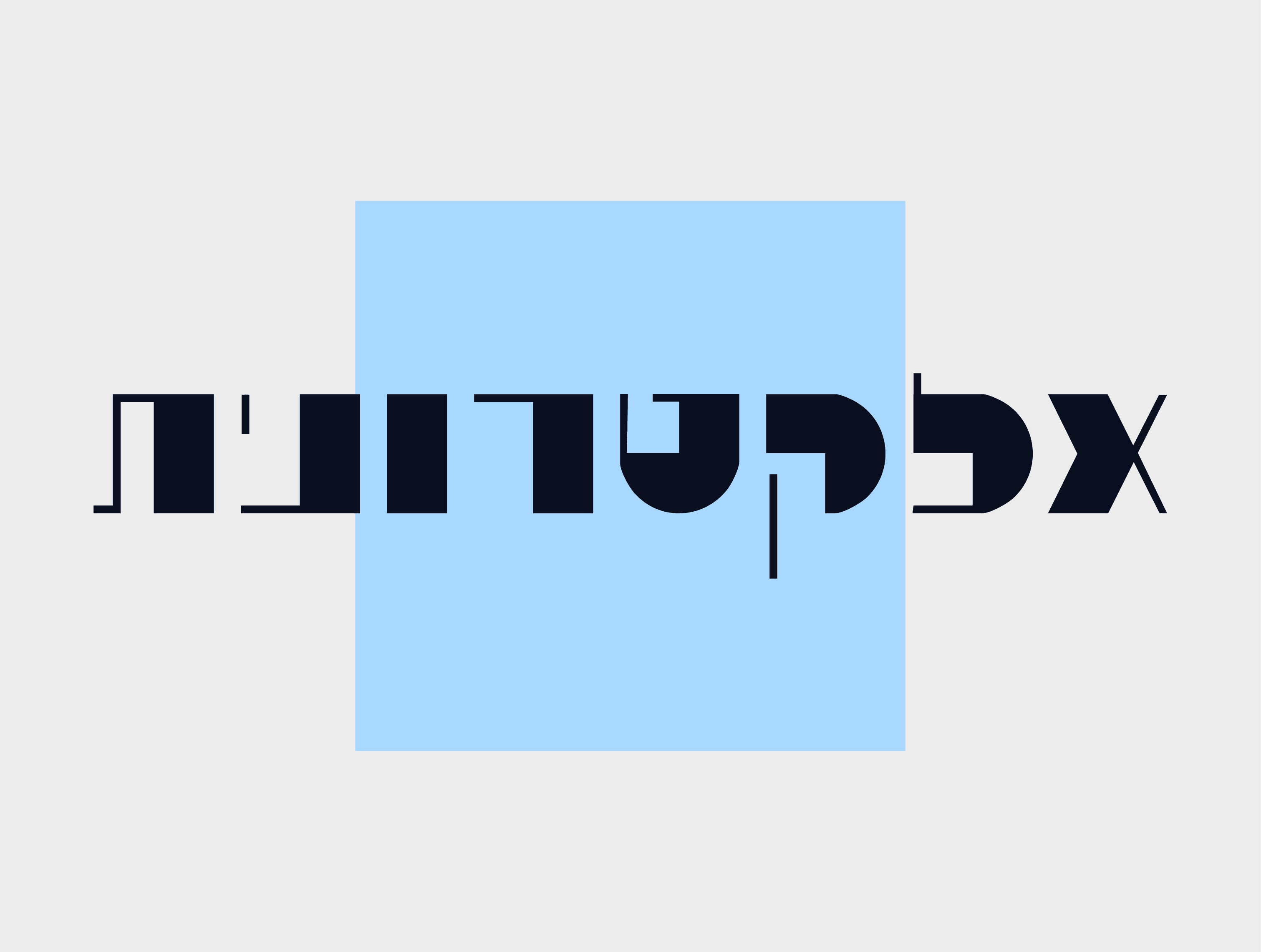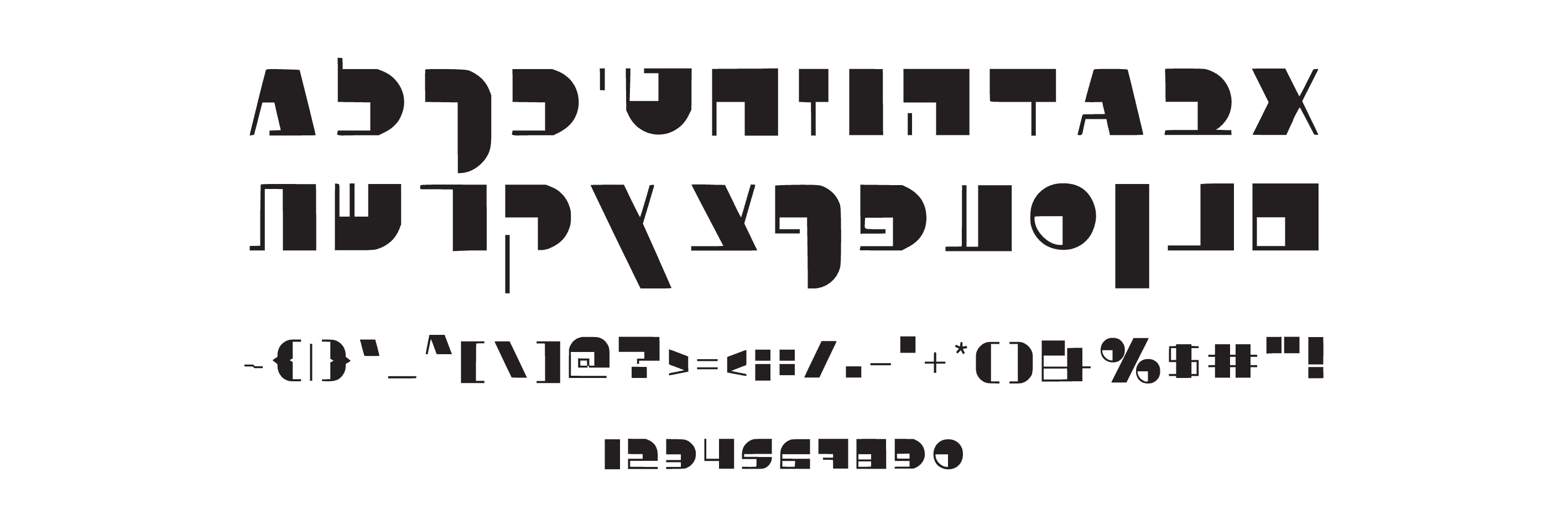
פונט אלקטרונית
פונט עברי גאומטרי ועתידני, מושלם לפוסטרים, עטיפות מוזיקה ועיצובי טכנולוגיה ניסיוניים.
אלקטרונית — הפונט מהעתיד (או מהמעבדה)
אלקטרונית הוא לא עוד פונט — הוא כלי גרפי רדיקלי.
פונט עברי גאומטרי, מקוטע ומדויק, שנראה כאילו נבנה במעבדת עיצוב עתידנית.
כל אות בפונט הזה היא יצירה בפני עצמה — שילוב של צורות בסיסיות כמו ריבועים, קווים וחצאי עיגולים, שיוצרים תחושה חדה, חדה מאוד.
זהו פונט שמיועד למעצבים אמיצים, כאלה שלא מפחדים מהפשטה וממראה קונספטואלי מובהק.
איפה הוא מרגיש בבית?
⚡ פוסטרים ניסיוניים ואמנותיים
⚡ עטיפות מוזיקה אלקטרונית
⚡ עיצובים למיתוגים טכנולוגיים-עתידניים
⚡ תערוכות חדשנות, דיגיטל ומדע
למי הוא מתאים?
למעצבים קונספטואליים, לחובבי עיצוב גאומטרי ניסיוני, ולכל מי שלא מפחד לשבור מוסכמות.